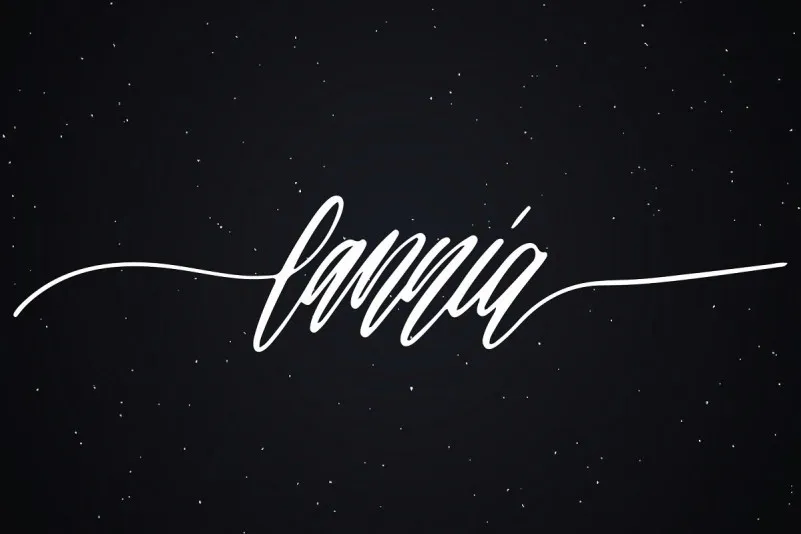
Lannia Handwritten Font
A Lannia Handwritten Font é uma elegante escolha para quem procura um script handwritten que combina feminilidade com modernidade. Com sua delicada atmosfera e atitude casual, essa fonte é perfeita tanto para criações minimalistas quanto para design sofisticado. Perfeito para variados usos como cabeçalhos, assinaturas, logotipos, convites vintage de casamento, camisetas, cartas de visita, sinalização, rótulos, noticiários e panfletos. Essa fonte tem um tom aconchegante que permite o texto ser lido facilmente, mas também oferece um toque elegante para adicionar sofisticação às suas criações. Não importa se você está trabalhando em design gráfico de moda, arte, ou até mesmo em criação de conteúdo digital – a Lannia Handwritten Font se adequa perfeitamente. Tornará seu trabalho ainda mais especial e único.